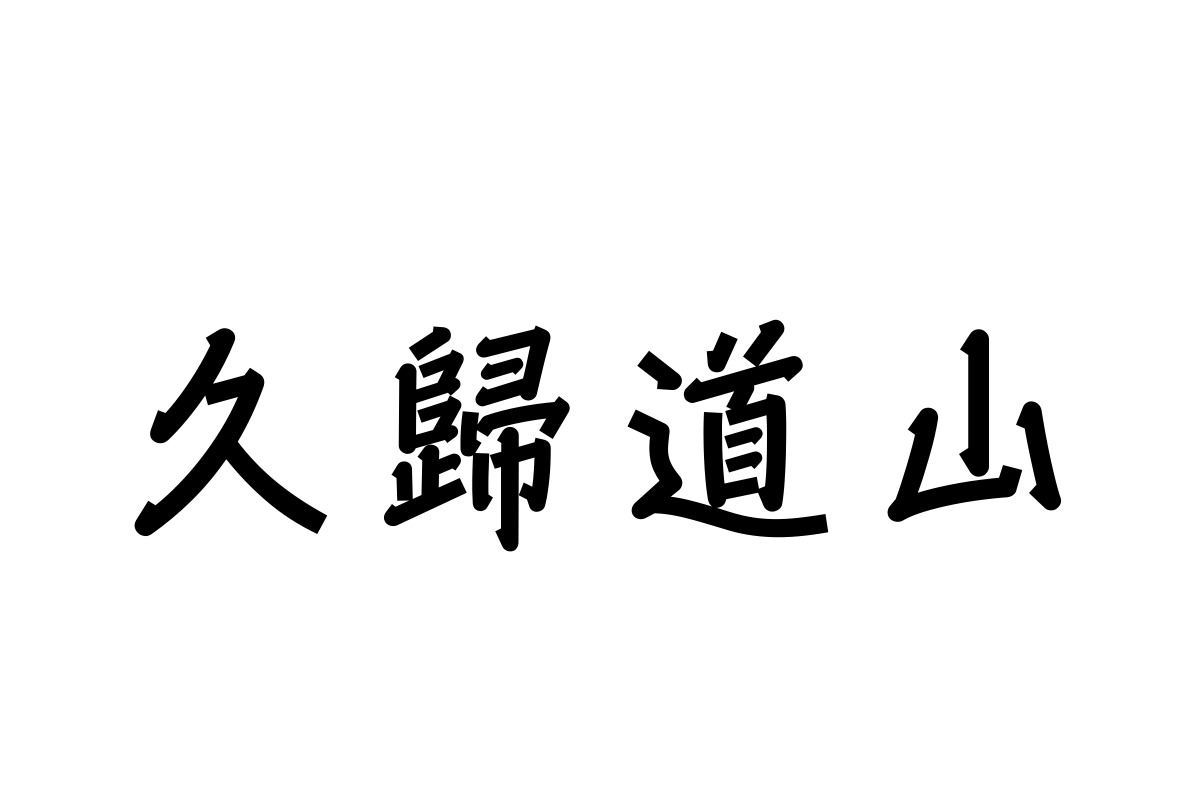
汉仪洛神行55繁的设计灵感来源于赵孟頫行书《洛神赋》卷,在字形结构上寻求“竦轻躯以鹤立,若将飞而未翔”的意境。该字体结合现代等线的笔画设计,保留了行楷的流畅潇洒,同时减弱了古旧气息。汉仪洛神行55繁的家族化设计包含5款字重,细款纤韧轻盈,粗款流畅厚重,适合不同场景的需求。
总的来说,汉仪洛神行55繁是一款具有独特设计和广泛应用的商业字体。